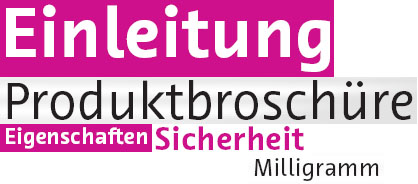
GELÖST Hausschrift Schering gesucht
Hat jemand eine Idee, ob das eine Corporate Font ist oder ansonsten, wie die Schriftart heisst? Ich kann nichts dazu im Web finden.
Wenn Du Dir mal ein PDF von Schering im Web suchst und im Acrobat Reader unter Eigenschaften nachschaust, kannst Du feststellen, daß Schering offensichtlich eine Hausschrift namens Schering Sans benutzt.
Bin leider erst Typo-Neuling, deswegen bin ich auf so etwas nicht gekommen.
Ich nehme an, dass diese Schrift demnach nicht erhältlich ist ...
Well, "Exclusive Custom Typeface" sagt es ja schon ...
Kennt jemand eine ähnliche Schrift? Ich finde die mega gut.
:oops: Na ja, vielleicht nicht im typografischen Sinn - wie gesagt, ich bin Neuling in der Typografie. Aber so im Layout gefällt sie mir optisch ziemlich gut. :oops:
Das könnte dir gefallen:
FF Absara (und Sans)
FF Quadraat (und Sans)
FF Eureka (und Sans)
Fedra (und Sans)
Ui, die Eureka ist klasse! Danke vielmals :D
Irgendwie ist die Schrift hier nicht so kantig.
mit der übernahme durch beyer dürften die fonts
wohl erstmal in der schublade landen ... schade um
die arbeit!
Soweit ich informiert bin, bleibt der Schering-"Zweig" bei der eigenen CI.
Aber wenn nicht - vielleicht verkauft Alessio sie dann? Fänd ich mega gut :wink:
kann gut sein. am firmensitz in berlin haben sie aber zumindest
das alte logo gegen eins im bayer-style getauscht ...
Schering gehört jetzt zu einer Untergruppe von Bayer: Bayer Schering Pharma. Das Brief-Layout usw. ist Bayer angepasst. Aber ich denke, dass die Produkte weiter mit dem alten Design laufen.
... ich habe mich nun für die Rotis Sans Serif entschieden. 8)
Deswegen hatte ich ja nach Vorschlägen gefragt :wink: